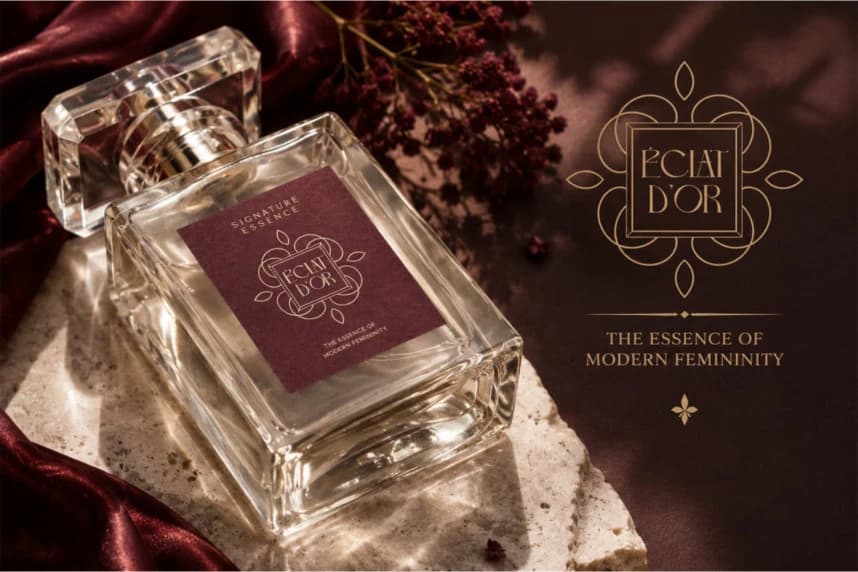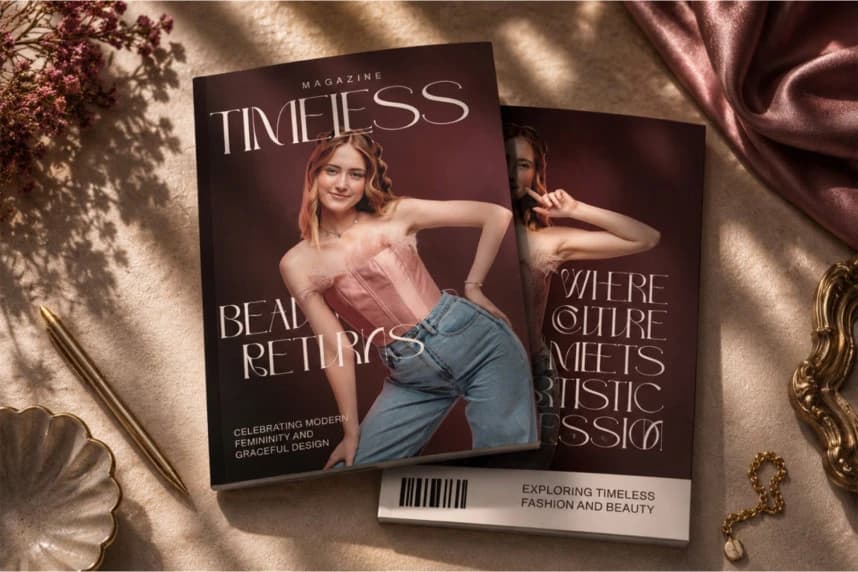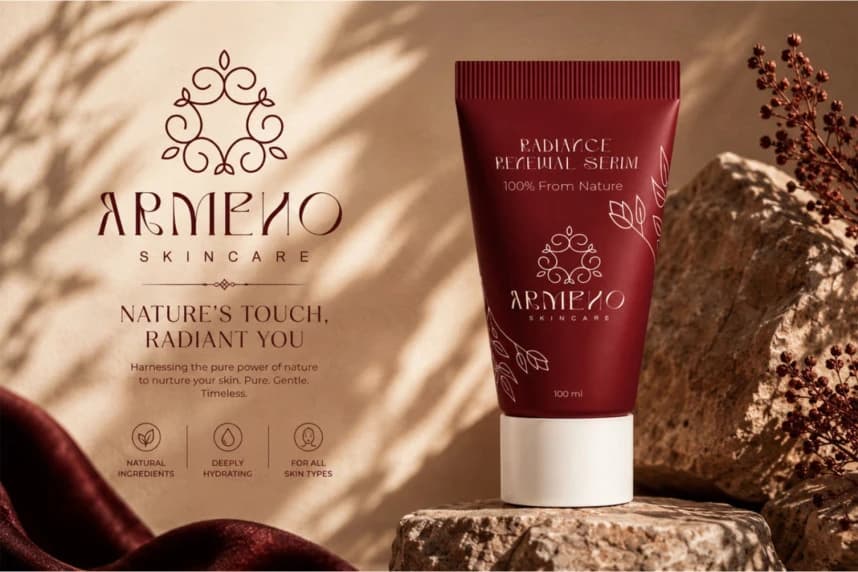
Arunela Font
Arunela Font, modern tipografiye zarafet, netlik ve sanatsal karakter kazandırmak için tasarlanmış zarif bir lüks display serif yazı tipidir. İnceliğiyle.
Arunela Font, modern tipografiye zarafet, netlik ve sanatsal karakter katmak için tasarlanmış zarif bir lüks gösterişli serif yazı tipidir. İnce işçiliğiyle